10 кириллических шрифтов, чтобы подписывать открытки и подарки
Делимся ссылками на десяток кириллических шрифтов, которые пригодятся тем, кто не любит подписывать подарки, открытки и приглашения от руки.
Не все из нас обладают идеальным почерком, да и вообще любят писать от руки. Для тех, кто хотел бы набирать открытки, приглашения и бирки для подарков на компьютере, мы выбрали десять бесплатных шрифтов с поддержкой кириллицы.
Charming
Рукописный шрифт, вдохновленный старым американским леттерингом. Подойдет для приглашений на хипстерскую вечеринку с крафтовым пивом.
Komi
Этнический шрифт. Таким хорошо подписать открытку, прилагающуюся к набору травяных чаев.
Iced tea
Оптимистичный и простой шрифт, которым можно и рукодельный подарок подписать, и мотивирующий постер набрать.
Katona
Еще один рукописный шрифт, на этот раз — тонкий и нежный, очень «открыточный».
Peteroque
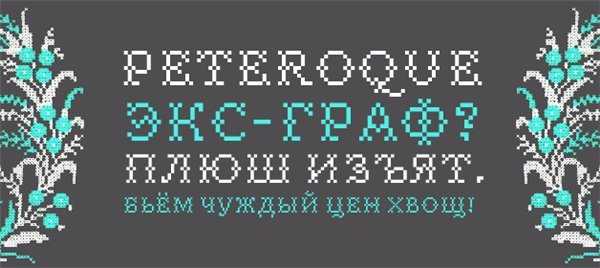
Вышитые крестиком буквы для самых душевных поздравлений и приглашений.
Legend
Средневековый шрифт для тематических подарков и вечеринок. Впрочем, как и остальные, его можно использовать без особого повода, ведь нам, в отличие от серьезных дизайнеров, можно «играть со шрифтами» как угодно.
Barkentina
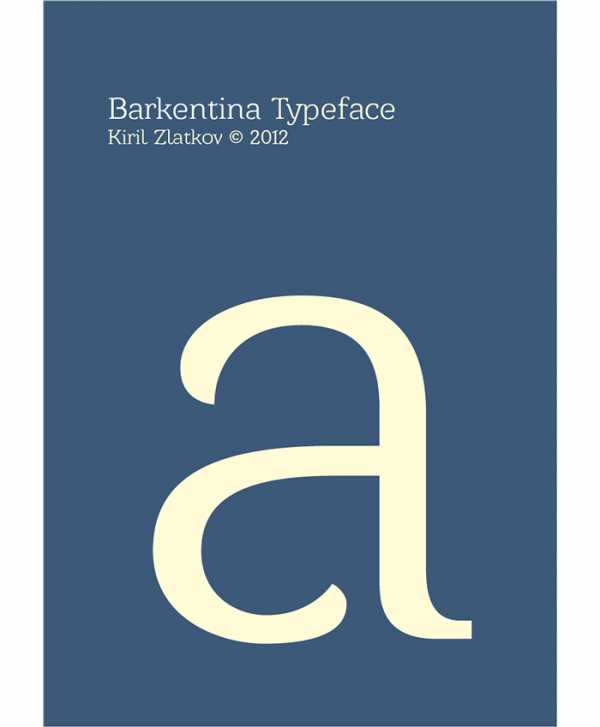
Элегантный шрифт для материалов в стиле ар-деко — так описывают его создатели. Понравится взрослым людям с хорошим вкусом.
Metropolis 1920
А вот это уже очевидное ар-деко: огни большого города, небоскребы, шикарная жизнь. Используйте, если собираетесь закатить вечеринку в стиле «Великого Гэтсби».
Douchepac
Экспериментальный иронический пиксельный шрифт, будто специально созданный для приглашений. Пробуйте разные цвета и сочетания обычного и жирного начертания.
Chehov
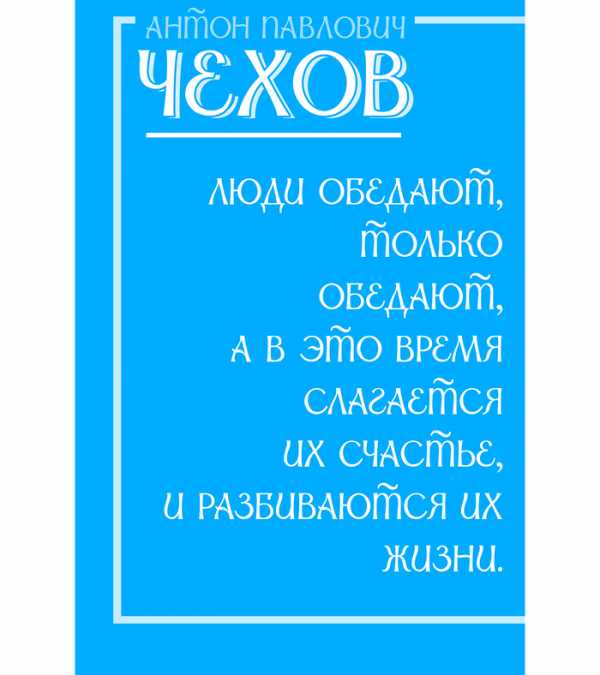
Русский шрифт, созданный специально для кириллицы. К сожалению, из знаков препинания только точка и запятая.
Chava
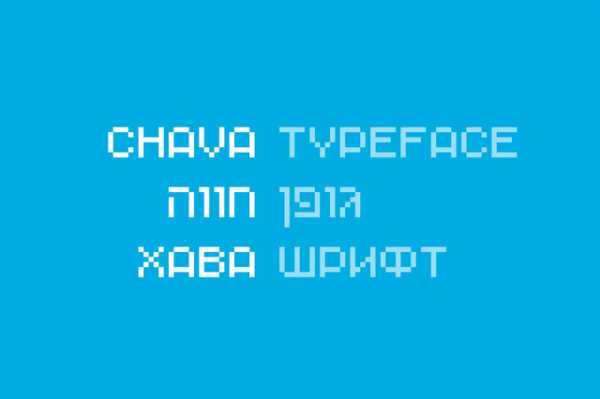
И еще один пиксельный шрифт, попроще, чем Douchepac.